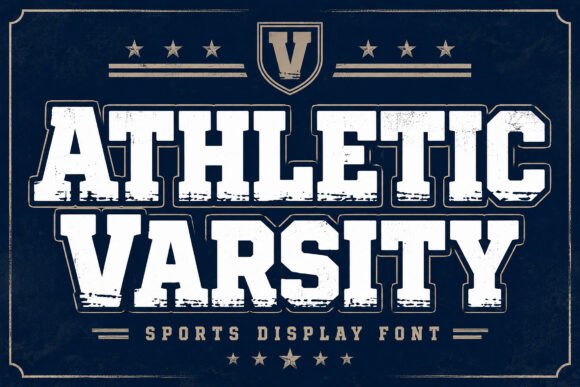
Athletic Varsity
Jika anda sedang mencari aset berkualiti tinggi seperti Athletic Varsity, pakej premium ini merupakan pilihan yang hebat untuk projek kreatif anda.
Dicipta dengan ketepatan, Athletic Varsity menyediakan vektor yang bersih, tipografi yang licin dan lesen komersial untuk ketenangan fikiran.
Sama ada anda mencipta produk POD (Print on Demand), jemputan perkahwinan atau grafik media sosial, Athletic Varsity amat bersesuaian.